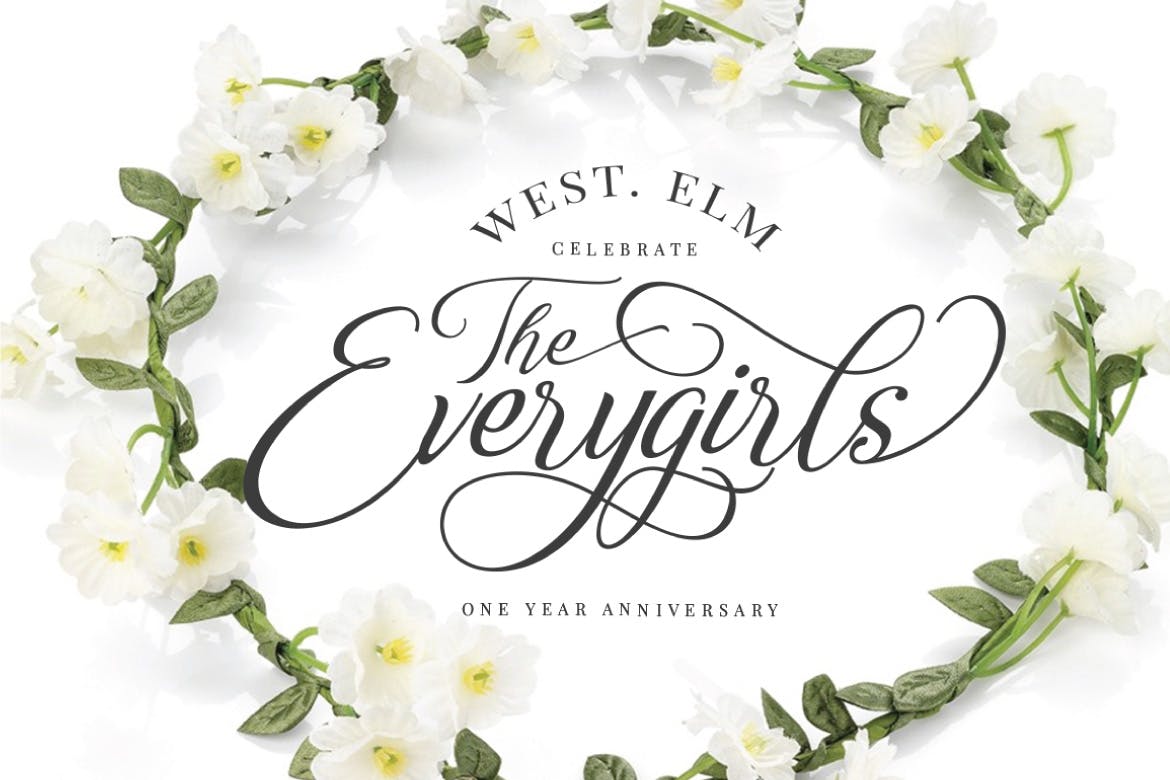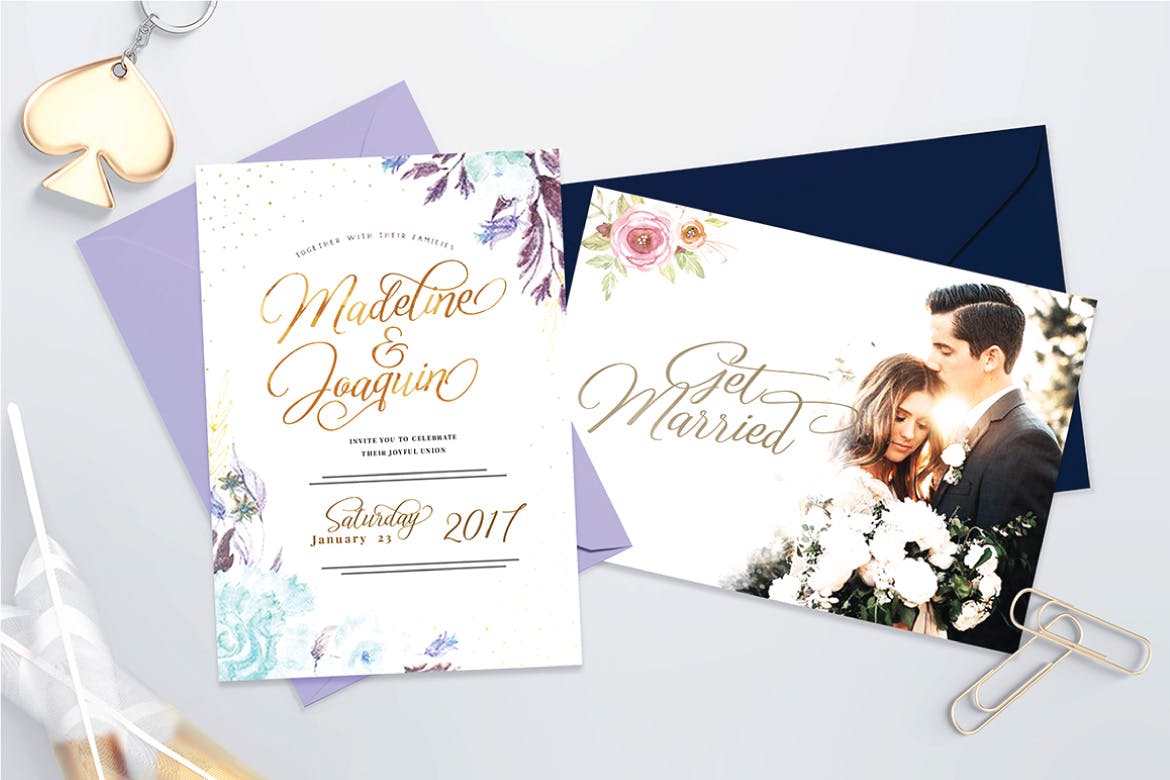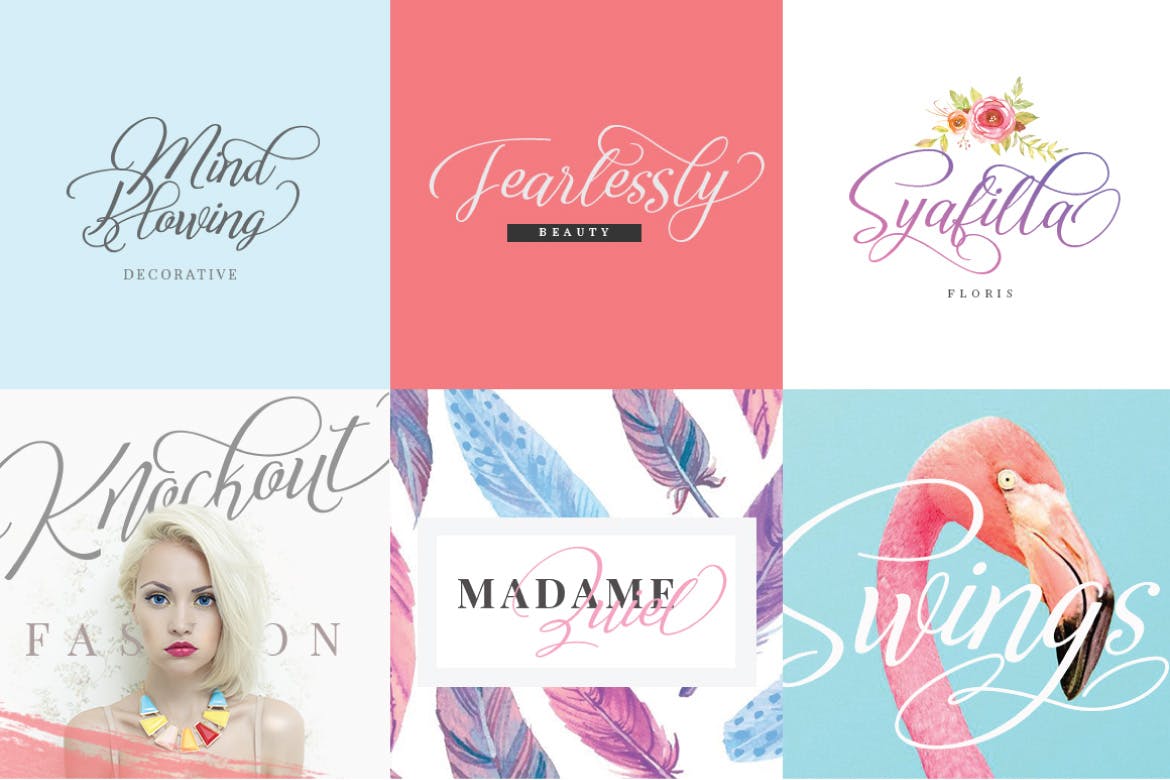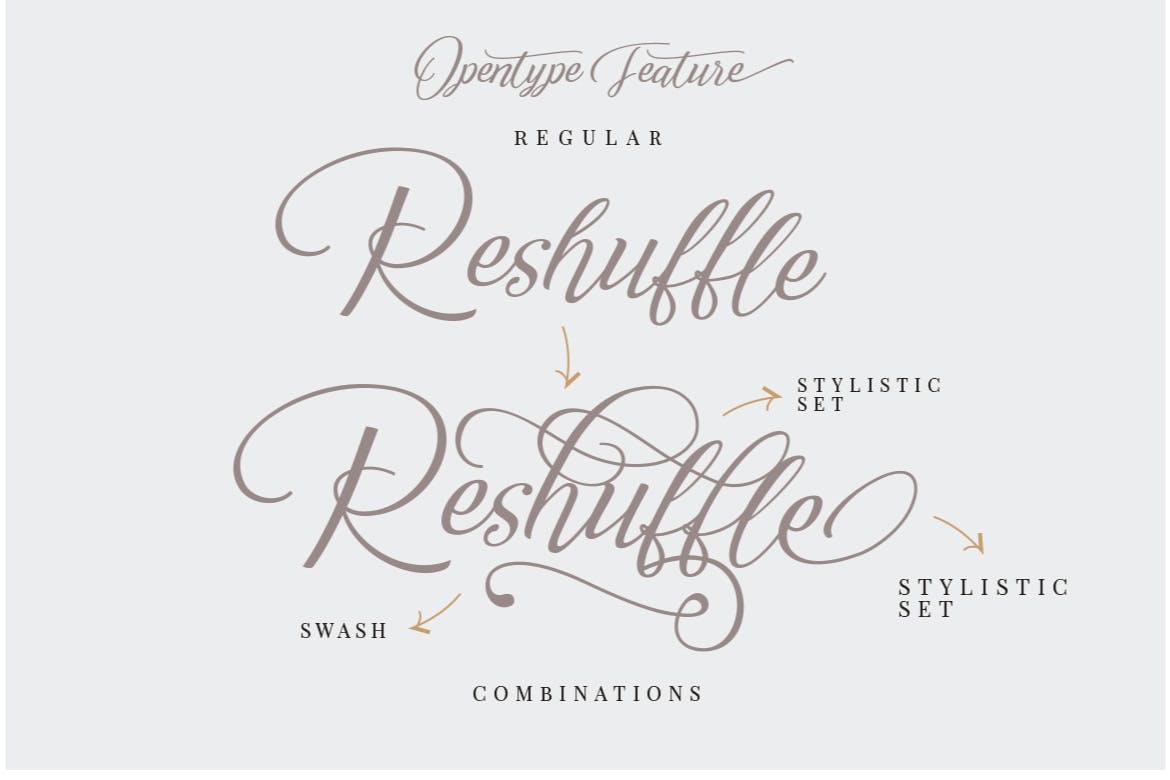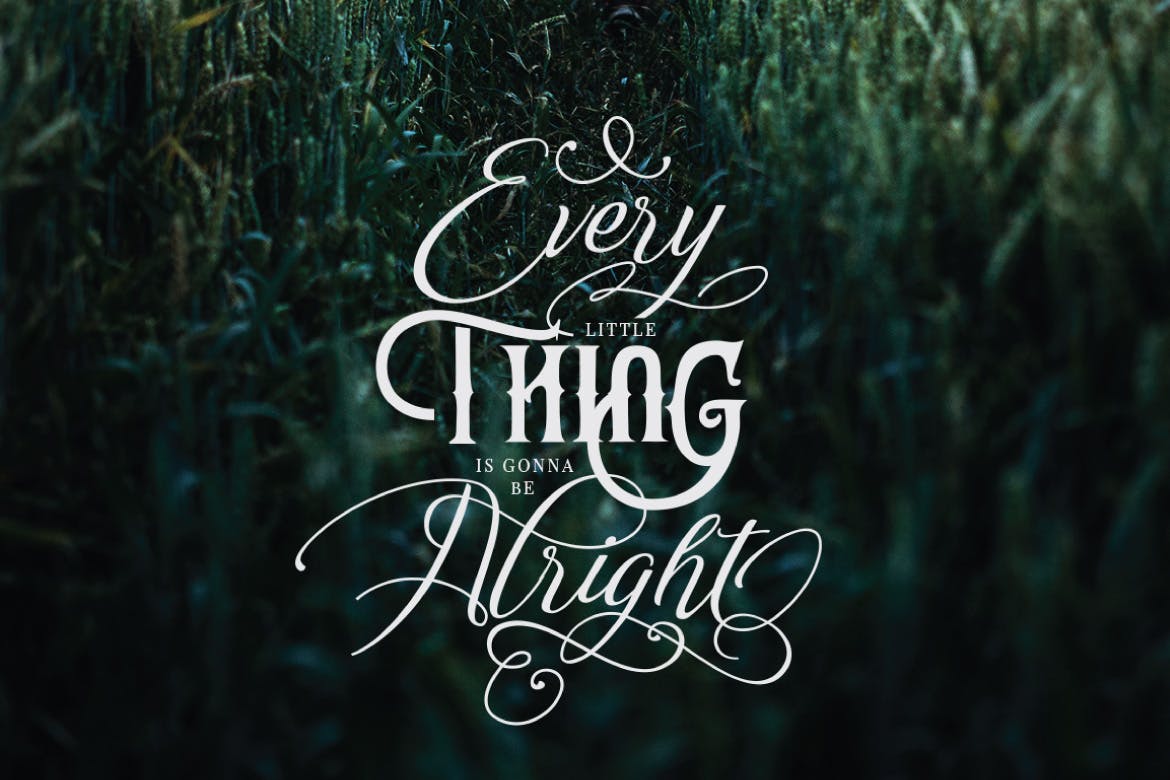
فونت Reshuffle - یک فونت جدید و مدرن با طراحی خطاطی، کاراکترهای تزئینی و بیسلاین رقصان! این فونت برای دعوتنامهها، کارتهای تبریک، مواد برندینگ، کارتهای ویزیت، نقلقولها، پوسترها و بسیاری موارد دیگر فوقالعاده زیباست!
فونت Reshuffle با ۴۴۸ گلیف اضافی عرضه میشود. کاراکترهای جایگزین به چندین ویژگی Open Type تقسیم شدهاند مانند ستهای استایلی، جایگزینهای استایلی و لیگاتور. ویژگیهای Open Type با استفاده از برنامههای حرفهای مانند Adobe Illustrator، Adobe InDesign، Adobe Photoshop، Corel Draw X و Microsoft Word قابل دسترسی هستند. این فونت دارای کدگذاری PUA یونیکد (فونتهای بهخصوص کدگذاری شده) است، به طوری که تمام کاراکترهای جایگزین به راحتی توسط یک هنرمند یا طراح قابل دسترسی میباشد.